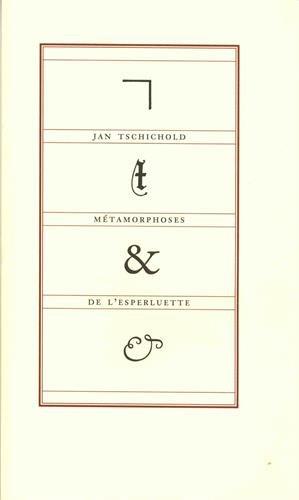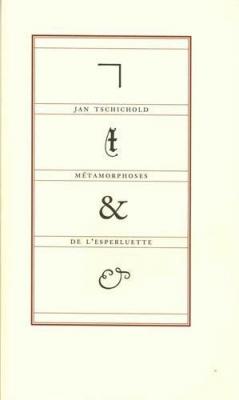
Livre neuf. Métamorphoses de l'esperluette. Petite étude historique et typographique de l'esperluette, mot-symbole issu du latin et correspondant au digramme "et", dont les premières formes sont trouvables sur des graffitis de Pompéi au premier siècle avant J-C. Traduction d'un texte du typographe Jan Tschischold, initialement publié en 1953, depuis l'allemand, par Julien Gineste. Postface de Marc H. Smith.